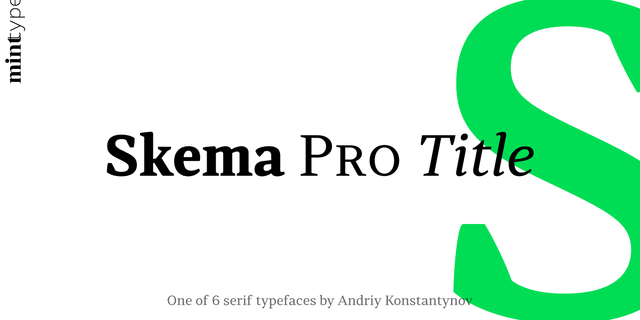
Skema Pro Title – среднеконтрастная гарнитура с большой высотой строчных и вертикальной осью. Предназначена для более крупных элементов, таких как подзаголовки и выноски.
Skema Pro – система из 6 антикв, каждая из которых имеет свой характер и назначение. Вместе они формируют огромную супергарнитуру из 84 начертаний для любых возможных задач.
Семейство Skema Pro разработал и выпустил Андрей Константинов в студии Mint Type в 2017 году.
Ассоциации c начертанием Skema Pro Title RegularКачества и характер:
спокойный, ровный, гармоничный, универсальный, понятный, простой, нейтральный, средний, обычный, деловой, уравновешенный, космополитичный, ненавязчивый, умеренный, техничный, современный, точный, логичный, неброский, практичный, оптимальный, доступный, статичный, культурный, образованный, устойчивый, строгий, серьезный, умный, твердый, четкий, резкий